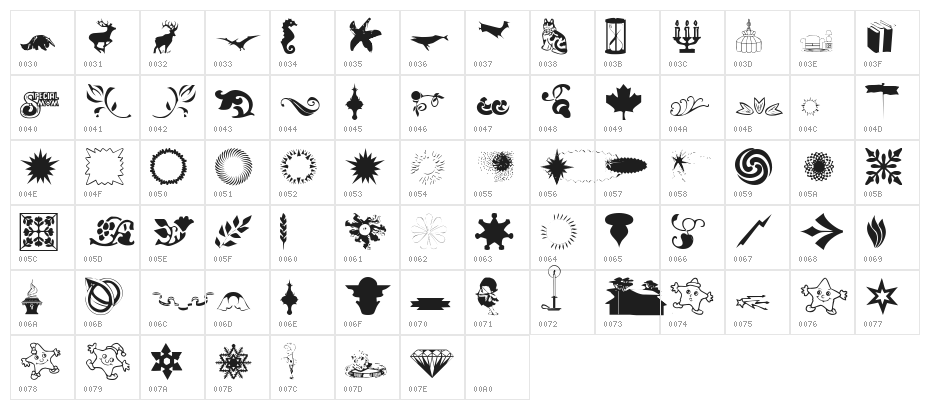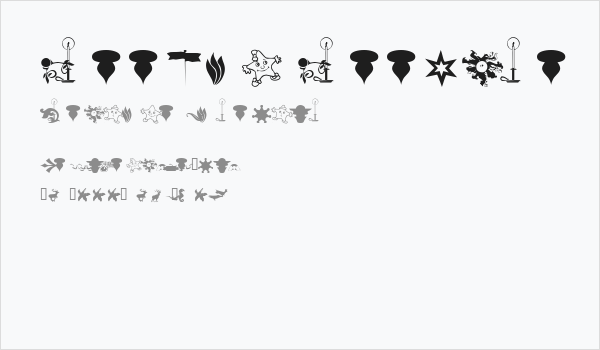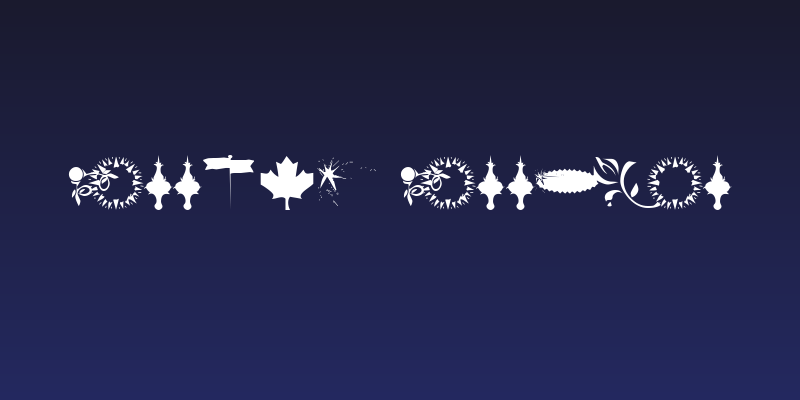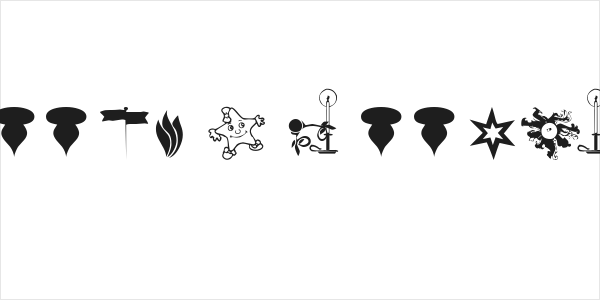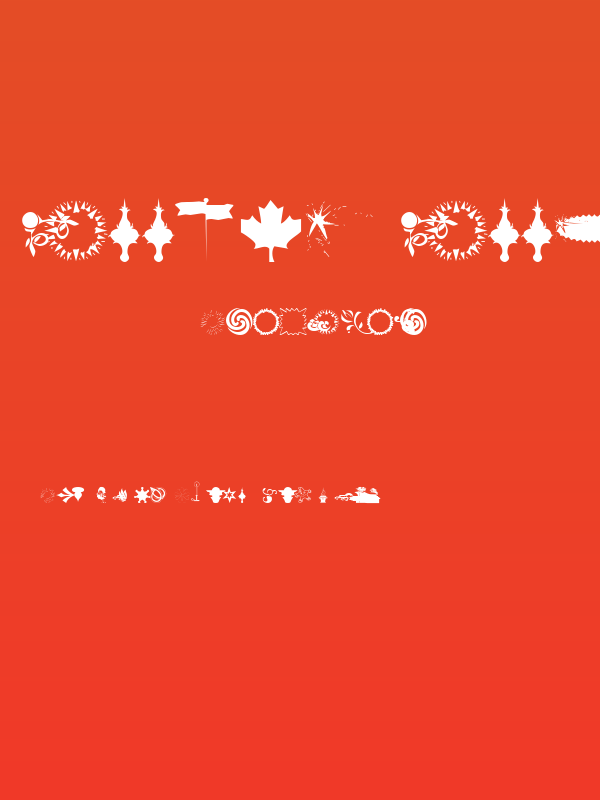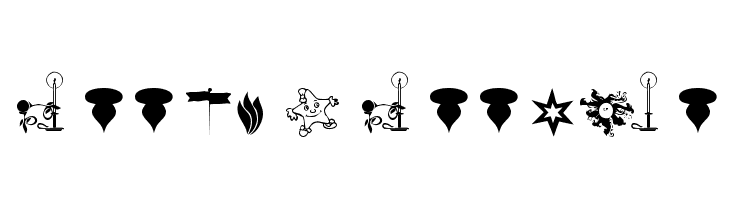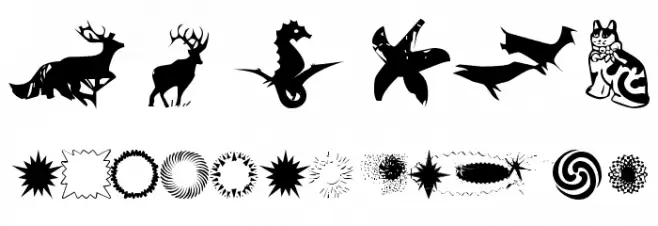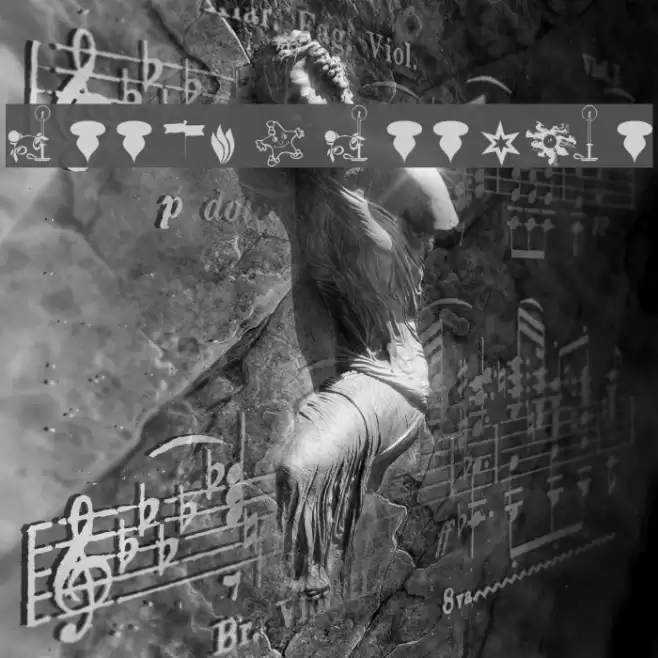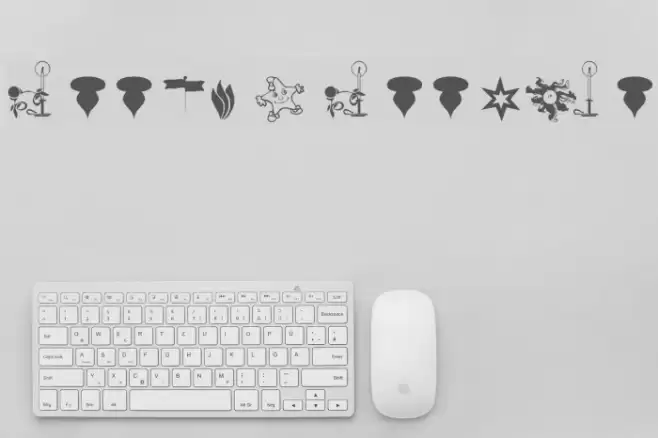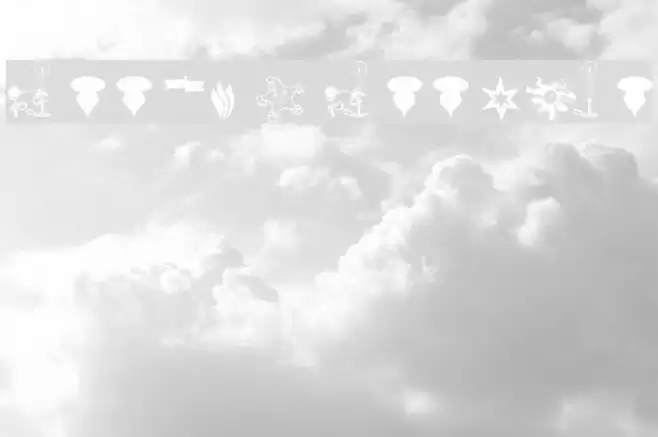
FreeMix Freeware Font
| 全体的なスタイル | Decorative, Playful, Eclectic |
| 用途 | Decorative elements, Icons, Borders, Illustrative accents |
| おすすめプロジェクト | Scrapbooking, party invitations, children's projects, logo embellishments, decorative borders, playful branding. |